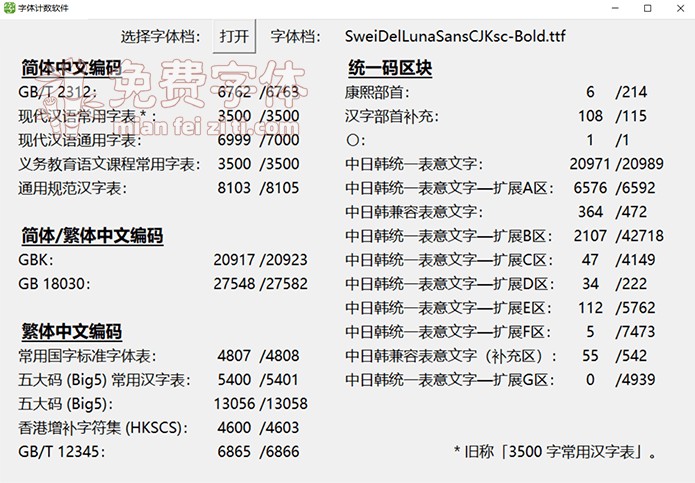
狮尾德鲁纳黑体:Max造字 改造思源黑体为像D形状免费商用字体资讯
狮尾德鲁纳黑体基于思源黑体的右侧变圆和拔脚改造,更加简明现代化的字体。支援简体中文、繁体中文、韩文与日文;可以免费商用,欢迎大家自由应用、自由优化、自由改作!
狮尾德鲁纳黑体与狮尾D露西差别在笔触是否有做调整,狮尾德鲁纳黑体所套用的效果较少,在笔触没有做调整。